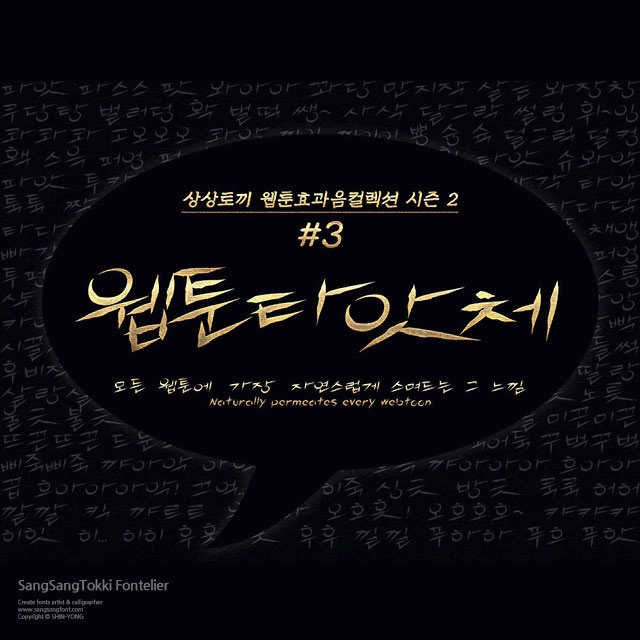
웹툰타앗체
상상토끼의 웹툰효과음컬렉션 시즌2 세번째, 웹툰타앗체
#3 웹툰타앗체 동작이 크고 역동적인 장면에 어울리는 웹툰콰앙체와 달리 섬세하고 예리한 액션 연출에 좋은 웹툰타앗체입니다. 어둡고 음침한 뒷골목 주먹들의 싸움이나 킬러물/느와르물의 날카로운 액션 연출이 필요할때 선택한다면 더할나위 없이 잘 어울리는 폰트입니다.